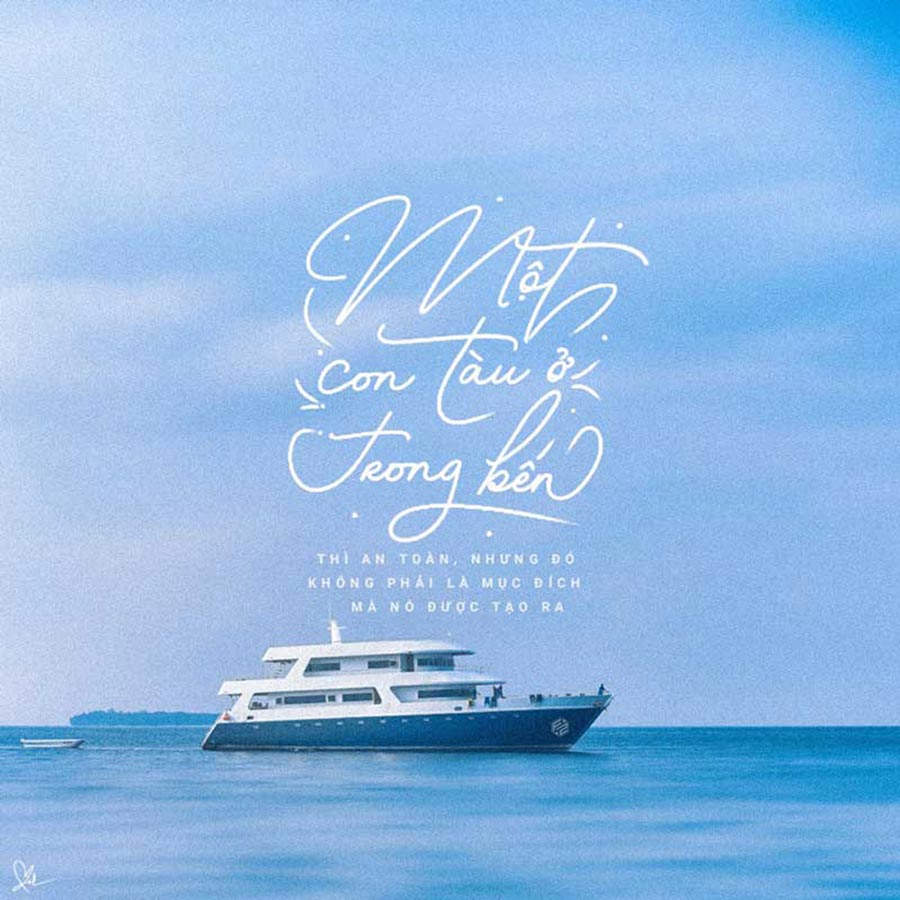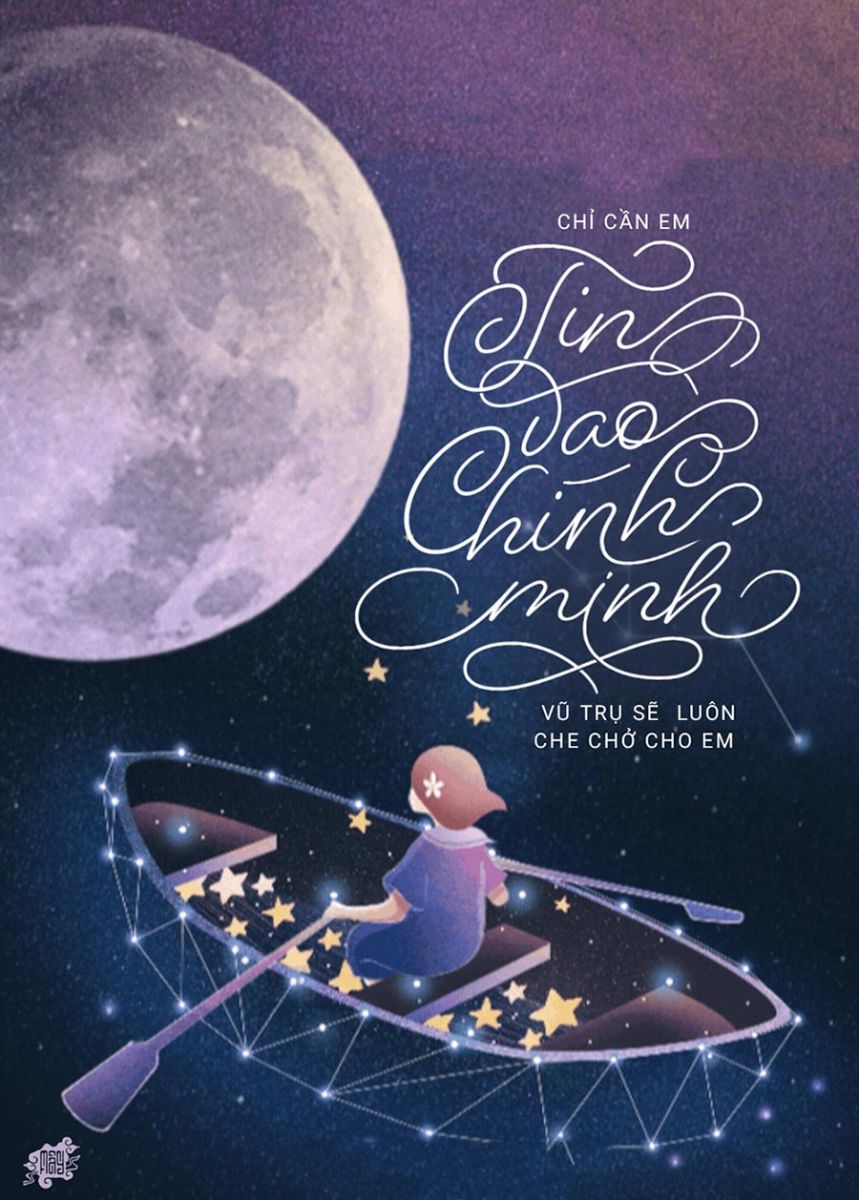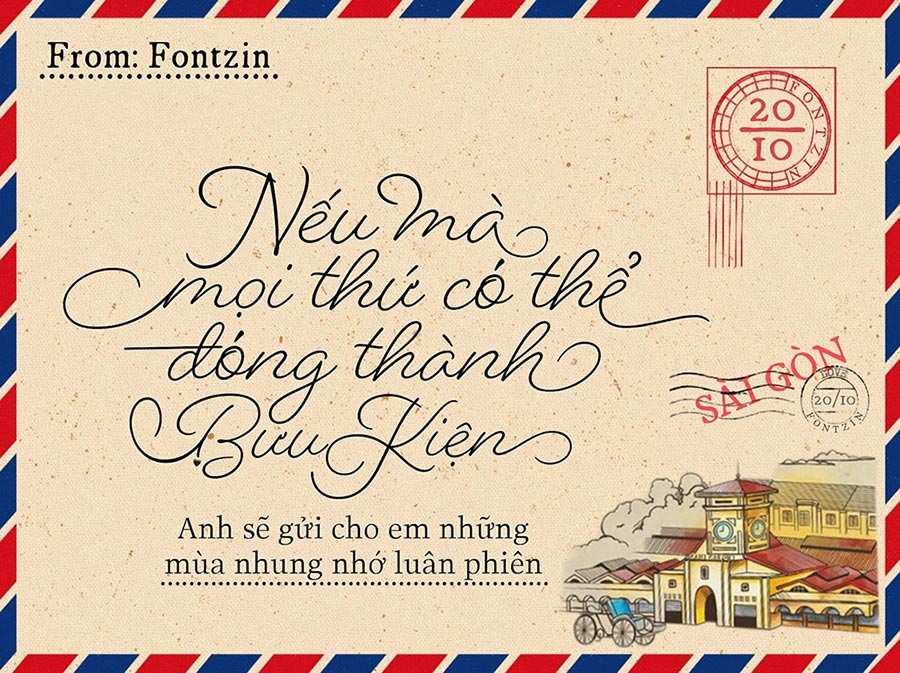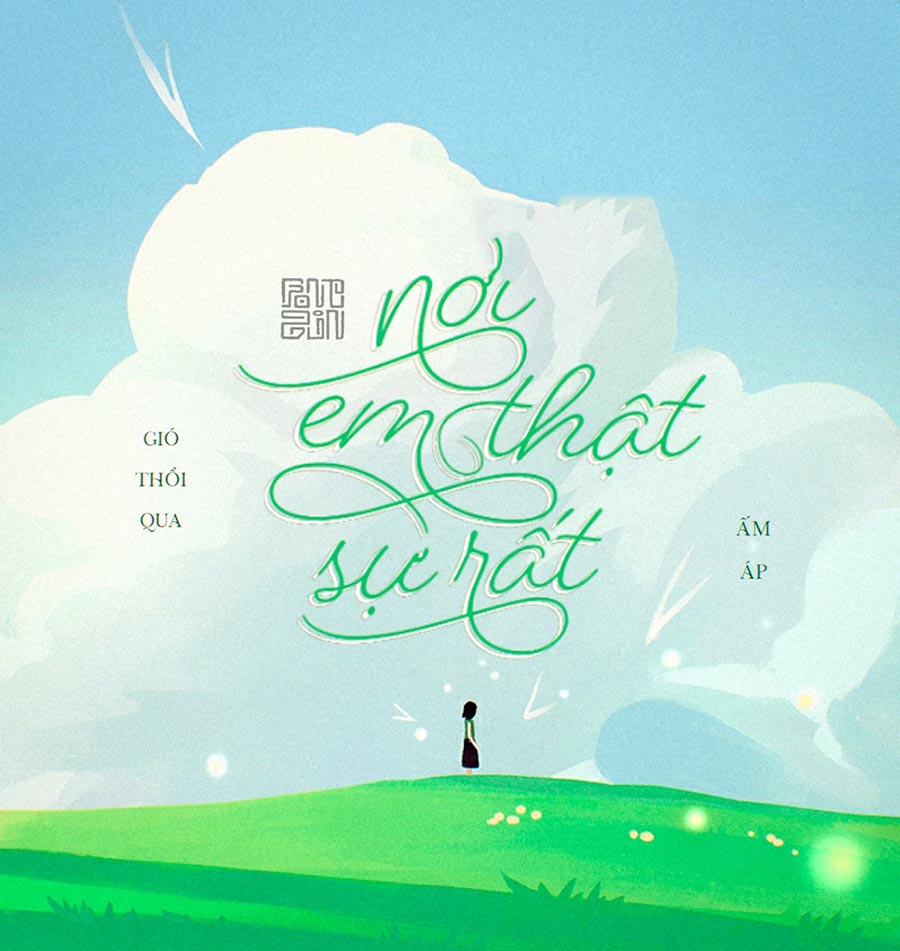
Chia Sẻ Miễn Phí Font Việt Hóa - Beloved Script Mang Phong Cách Cổ Điển Của Thế Kỷ 20
Sadesign.vn mang đến cho các designer một món quà tuyệt vời: font chữ Beloved Script Việt Hóa hoàn toàn miễn phí. Với phong cách cổ điển đậm chất thế kỷ 20, font Beloved Script nổi bật với các đường cong mềm mại, tạo cảm giác thanh thoát và sang trọng. Đây là sự lựa chọn lý tưởng cho các dự án thiết kế cần sự tinh tế và lịch lãm, từ thiệp mời, bìa sách cho đến các chiến dịch quảng cáo, giúp tăng thêm giá trị thẩm mỹ cho sản phẩm của bạn.
Giới Thiệu Về Font Beloved Script
Font Beloved Script là một trong những font chữ mang phong cách cổ điển, được thiết kế với các đường nét mềm mại và thanh thoát, mang đậm dấu ấn của thế kỷ 20. Phong cách viết tay uốn lượn của Beloved Script khiến nó trở thành một lựa chọn lý tưởng cho những dự án thiết kế cần sự sang trọng, thanh thoát. Phong cách cổ điển của Beloved Script không chỉ thu hút mà còn tạo nên sự tinh tế vượt thời gian. Cho dù bạn đang thiết kế thiệp cưới, logo thương hiệu, hay bìa sách, font Beloved Script sẽ luôn là sự lựa chọn giúp nâng tầm giá trị thẩm mỹ của sản phẩm.
Font Việt Hóa Beloved Script: Lợi Ích Khi Sử Dụng
Font Beloved Script mang đến sự kết hợp giữa phong cách viết tay cổ điển và các đường nét uốn lượn đầy nghệ thuật. Với bộ font này, mỗi sản phẩm thiết kế của bạn sẽ thể hiện được nét đẹp truyền thống và đậm chất cá nhân, thu hút sự chú ý từ người xem ngay từ cái nhìn đầu tiên. Một điểm mạnh khác của font Beloved Script là tính linh hoạt trong sử dụng. Font này có thể kết hợp với các font khác, tạo nên sự tương phản thú vị và làm nổi bật thông điệp mà bạn muốn truyền tải.